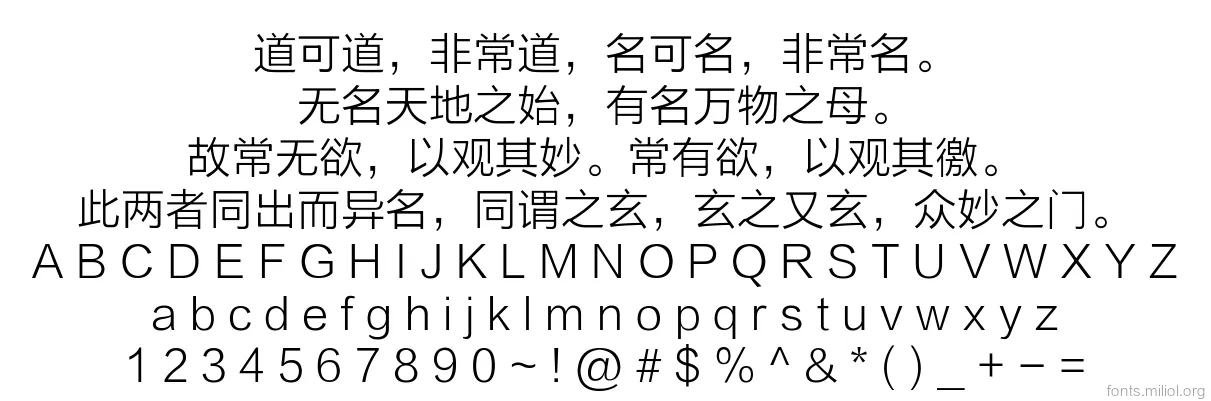
《方正兰亭细黑_GBK:优雅实用的中文字体》
方正兰亭细黑_GBK(FZLanTingHei-L-GBK)是一款兼具美学与功能性的专业中文字体,其设计灵感源自传统书法与现代排版需求的完美结合。该字体采用GBK编码标准,完整支持20902个汉字字符,确保在各类中文环境下的兼容性。其笔画纤细匀称,横平竖直间透露出东方韵味,特别适合用于正文排版、品牌标识和屏幕显示等场景。
作为方正字库的经典作品,兰亭细黑系列以"细而不弱"著称,0.75:1的严谨字面比例赋予文字独特的节奏感。字重适中,在8pt至14pt字号范围内保持优异的可读性,既不会因过细影响识别,也不会因过粗显得笨重。其西文字符部分采用无衬线设计,与中文字形和谐统一,满足双语混排需求。这款字体尤其适合追求简约现代风格的设计项目,能为各类视觉作品增添精致感。